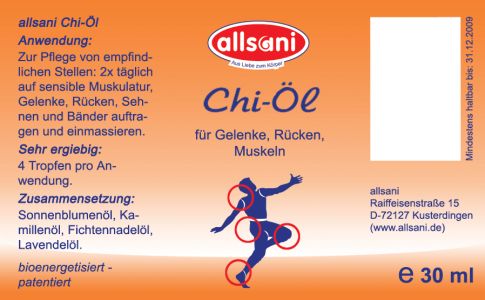
Hey Leute, da ich ncch relativ neu in dem Bereich der Typografie bin, brauche ich dringen eure Hilfe. Ich habe den Auftrag bekommen eine Etikettenserie zu machen :wink: bin aber mit der Typo noch nicht 100% zufrieden. Welche Schrift passt besser zu dem Logo? Hätte gerne eine Schreibschrift, die sehr gut Lesbar ist (Kunden von dieser Firma sind 40 aufwärts).
Na ja lange Rede kurzer Sinn. Hier ist der Entwurf des Etiketts. Größe der Etiketten: Chi-Öl: 47 x 77 mm; Elixier (jeweils): 50 x 95 mm
Es tut mir leid, aber was Du zeigst, ist indiskutabel.
Diese Arial-basierte „Typografie“ zur Diskussion zu stellen, geht nicht. Dieses Forum ist für fachliche (Detail-)Fragen gedacht und nicht, um Anleitungen zu geben, die uns alle arbeitslos machen.
Gestaltung macht der Gestalter. Wenn ich gute Gestaltung möchte, beauftrage ich einen.
Wenn ich Ackerschachtelhalm-Nährkonzentrat möchte, gehe ich ja auch nicht mit einem Strauß Ackerschachtelhalm zu allsani und frage, wie ich daraus ein Konzentrat herstelle ...
Und ich dachte immer Übung macht den Meister :cry:
Schreibschrift würde ich den Leuten hier nicht antun, vor allem weil bei solchen Etiketten am Ende immer mehr draufsteht als man anfangs geplant hat, und so alles immer gedrängter wird.
Oder die FF Sari?
Allerdings würde ich die Farbigkeit vielleicht überdenken: Blau-Orange ist nicht gerade die Chi-Ruhe-für-Gelenke-Farbkombination.
Generell lässt sich sowas aber (wie etwas unfreundlich ausgedrückt) nicht in einem Forum und auf die Schnelle lösen. Deshalb bitte die Vorschläge nur als Experiment-Vorschläge nehmen, ohne Garantie dass da auch was draus wird in der praktischen Gestaltung.
Cool Danke, werde mal die Schrift aussuchen, und bedanke mich für deine schöne Antwort. Ich habe bei meiner ANfrage eigentlich aber eher an die "Überschriften", also Elixier und Chi-Öl gedacht.